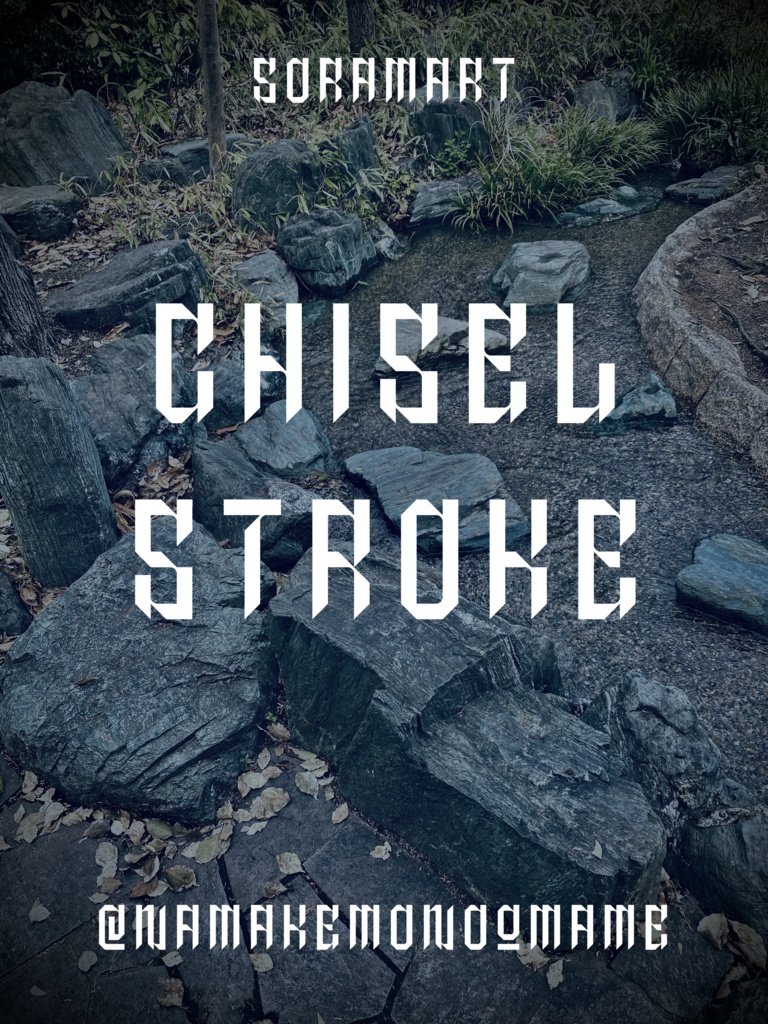
そらマートフォントデータ”Chisel Stroke”Digital2,500 JPYAdd to CartBuy a GiftAbout Gift彫刻刀で刻んだような斜線をモチーフにしたフォント "Chisel Stroke" です。 「TrueTypeフォントファイル」という形式です。 ダウンロードした後、Zipファイル内のデータをインストールしてお使いください。 このフォントは商用利用可となっております。 お客様の制作・創作活動のお役に立てれば幸いです。 ※使用上の注意事項などは、添付のReadmeをお読みください。そらマートVisit FANBOX!Fontsフォントデータ”RANMMA Drive”そらマート0 JPYFontsフォントデータ”Dandy Laser Max”そらマート2,500 JPYFontsフォントデータ”Dandy Laser”そらマート2,500 JPYFontsフォントデータ”Bubblegum Beat”そらマート2,500 JPYFontsフォントデータ”Caltrop Serif LLL”そらマート2,500 JPYFontsフォントデータ”Caltrop Serif LL”そらマート2,500 JPYFontsフォントデータ”Caltrop Serif”そらマート2,500 JPYFontsフォントデータ”Tonik Crate Super Long”そらマート2,500 JPYFontsフォントデータ”Dot Eat Bug Acid”そらマート2,500 JPYFontsフォントデータ”Dot Eat Bug Mild”そらマート2,500 JPYFontsフォントデータ”Dot Eat Bug”そらマート2,500 JPYFontsフォントデータ”Solid Voltage Strike”そらマート2,500 JPYFontsフォントデータ”Solid Voltage”そらマート2,500 JPYFontsフォントデータ”Henge Edge Rock”そらマート2,500 JPYFontsフォントデータ”Henge Edge Tall”そらマート0 JPYFontsフォントデータ”Henge Edge”そらマート0 JPYFontsフォントデータ”Chisel Stroke Wide”そらマート2,500 JPYFontsフォントデータ”Crushed Can Serif Empty”そらマート2,500 JPYFontsフォントデータ”Crushed Can Serif Wide”そらマート2,500 JPYFontsフォントデータ”Crushed Can Serif”そらマート2,500 JPYSee More